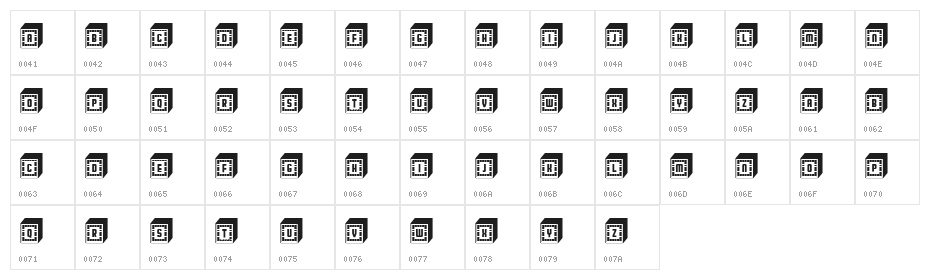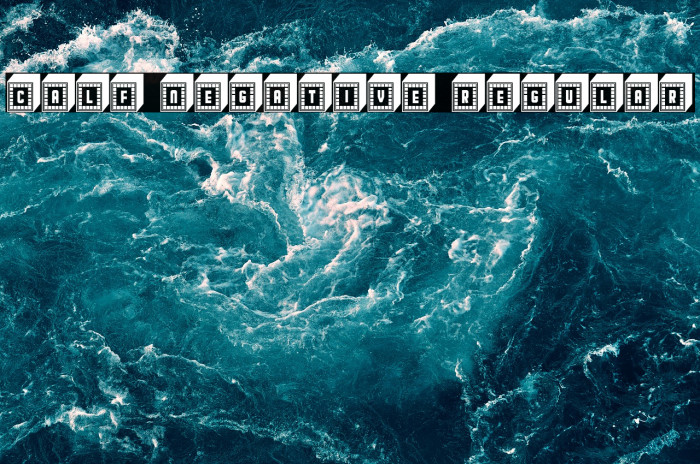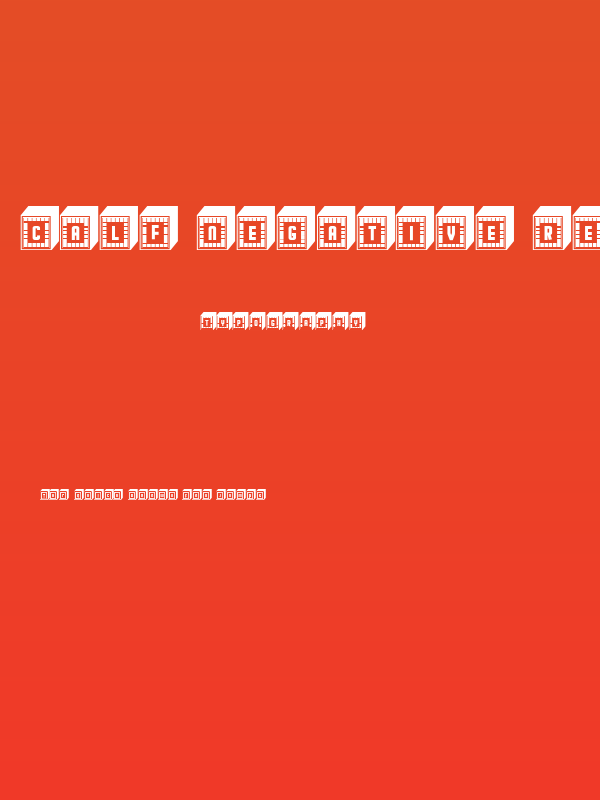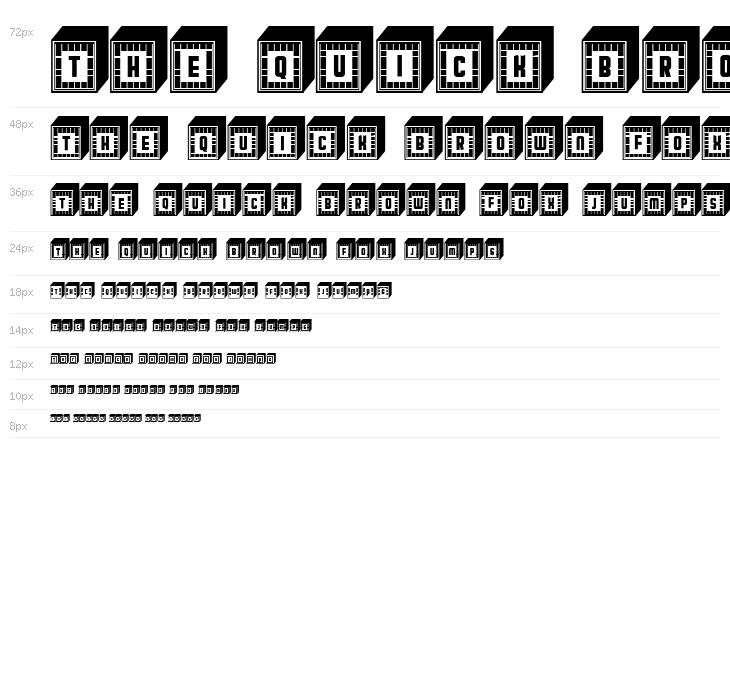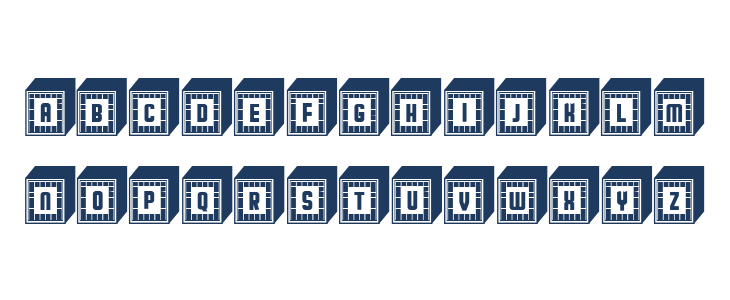
Calf Negative Regular Font
| Gesamtstil | Retro, Decorative |
| Vorgeschlagene Projekte | Ideal for retro-themed designs, posters, signage, and branding projects that require a strong visual presence. |